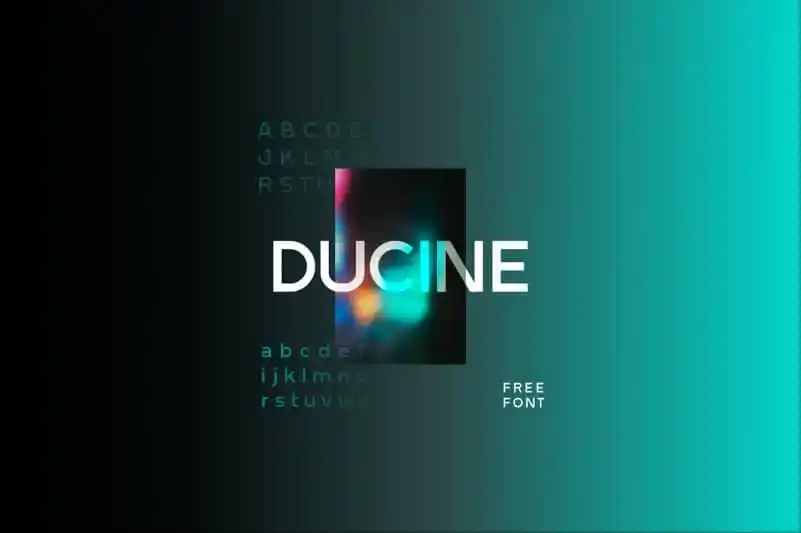
DUCINE Sans Serif Font – Download Grátis
A DUCINE Sans Serif é uma fonte moderna e distintiva para sinóticas serifadas que se destaca no mercado. Perfeita tanto para textos informativos quanto para design gráfico, essa fonte pode ser facilmente aplicada em diversos contextos. Seja você um designer de logotipos ou um editor de websites, a DUCINE Sans Serif é uma excelente opção para adicionar um toque moderno e distintivo ao seu projeto. Suas linhas leves e elegantes garantem que sua mensagem seja percebida de forma clara e profissional em qualquer aplicação visual. Ideal tanto para textos detalhados quanto para estilos simples, a DUCINE Sans Serif é uma excelente escolha para qualquer projeto onde você procura um equilíbrio entre modernidade e elegância.